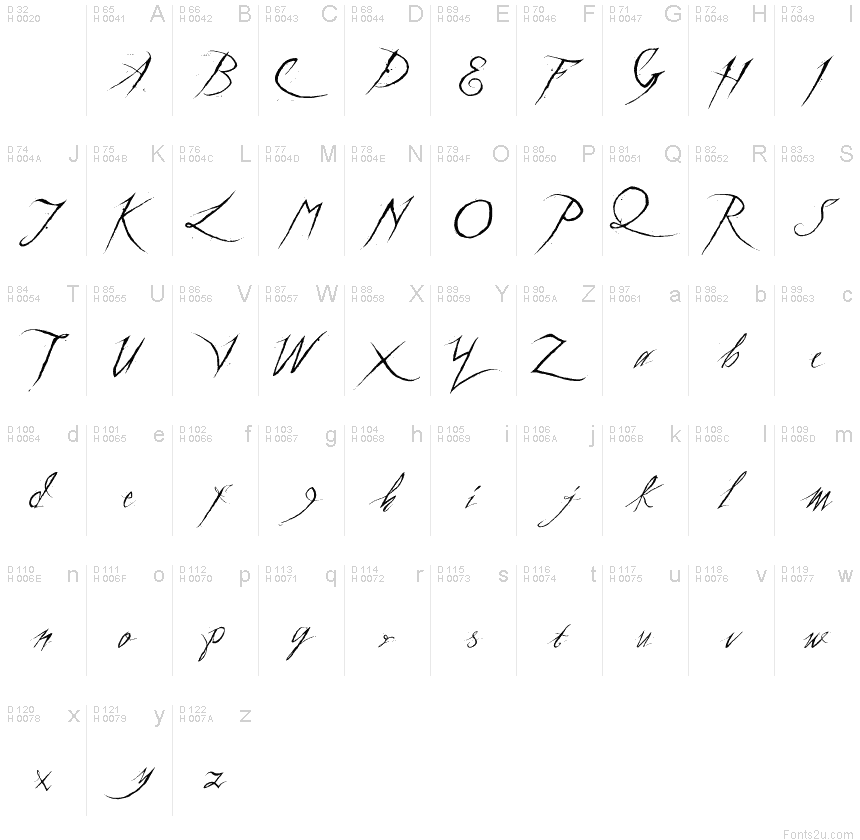
A Theme for Murder to urzekający krój kaligraficzny zaprojektowany przez Christophera Hansena. Jego śmiałe, zamaszyste pociągnięcia i dramatyczne zdobienia przywodzą na myśl aurę tajemnicy i intrygi, dzięki czemu stanowi idealny wybór dla szerokiego spektrum projektów graficznych. Od okładek książek po plakaty filmowe – wyrazista estetyka tego kroju nadaje każdemu projektowi nutę wyrafinowanej elegancji. Jego wszechstronność sprawdza się również w brandingu, oznakowaniu i zaproszeniach, gdzie unikalny charakter dodaje poczucia ekskluzywności i wyrafinowania.
A Theme for Murder to bez wątpienia krój, który przykuwa uwagę i pozostawia trwałe wrażenie.